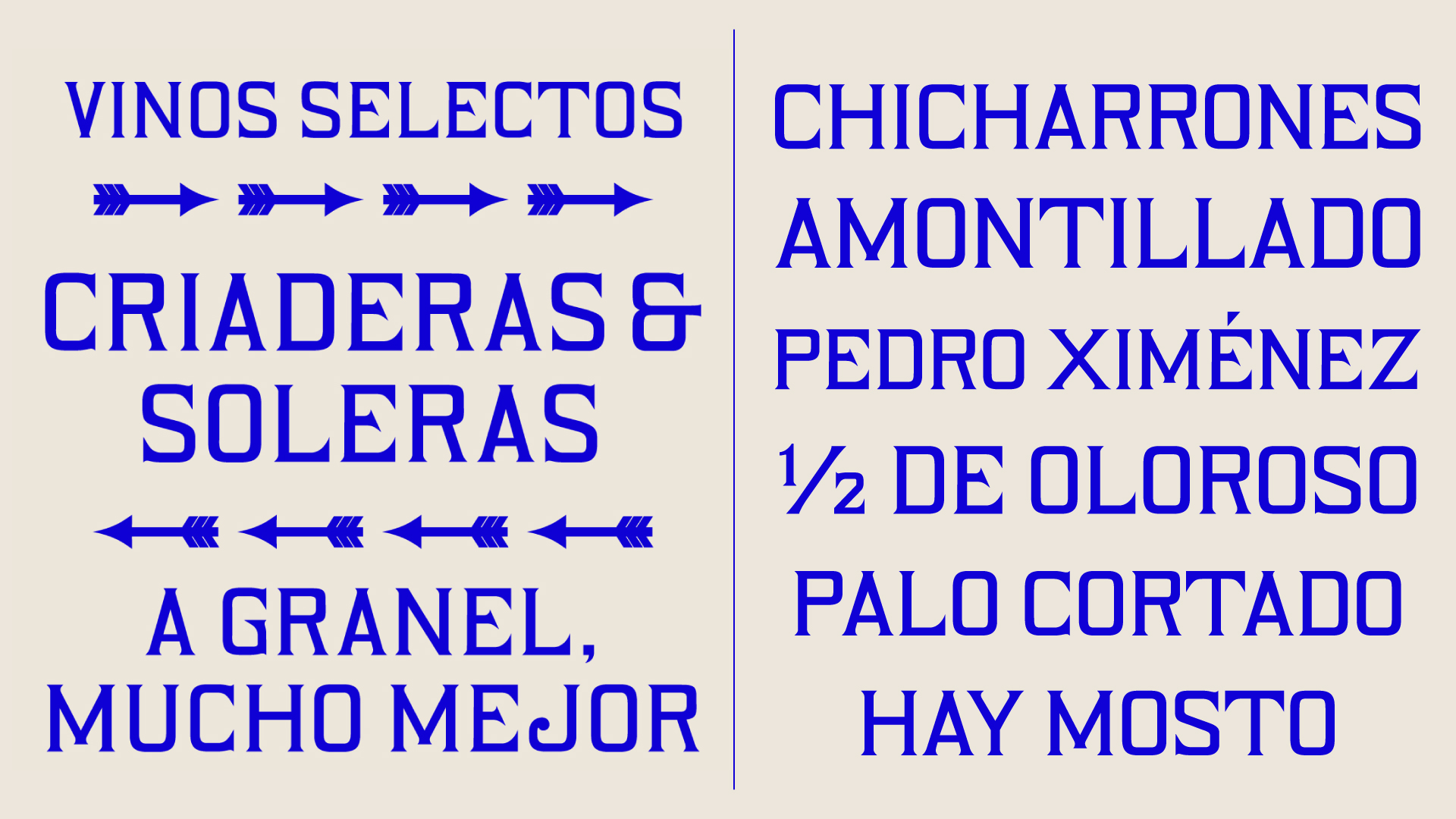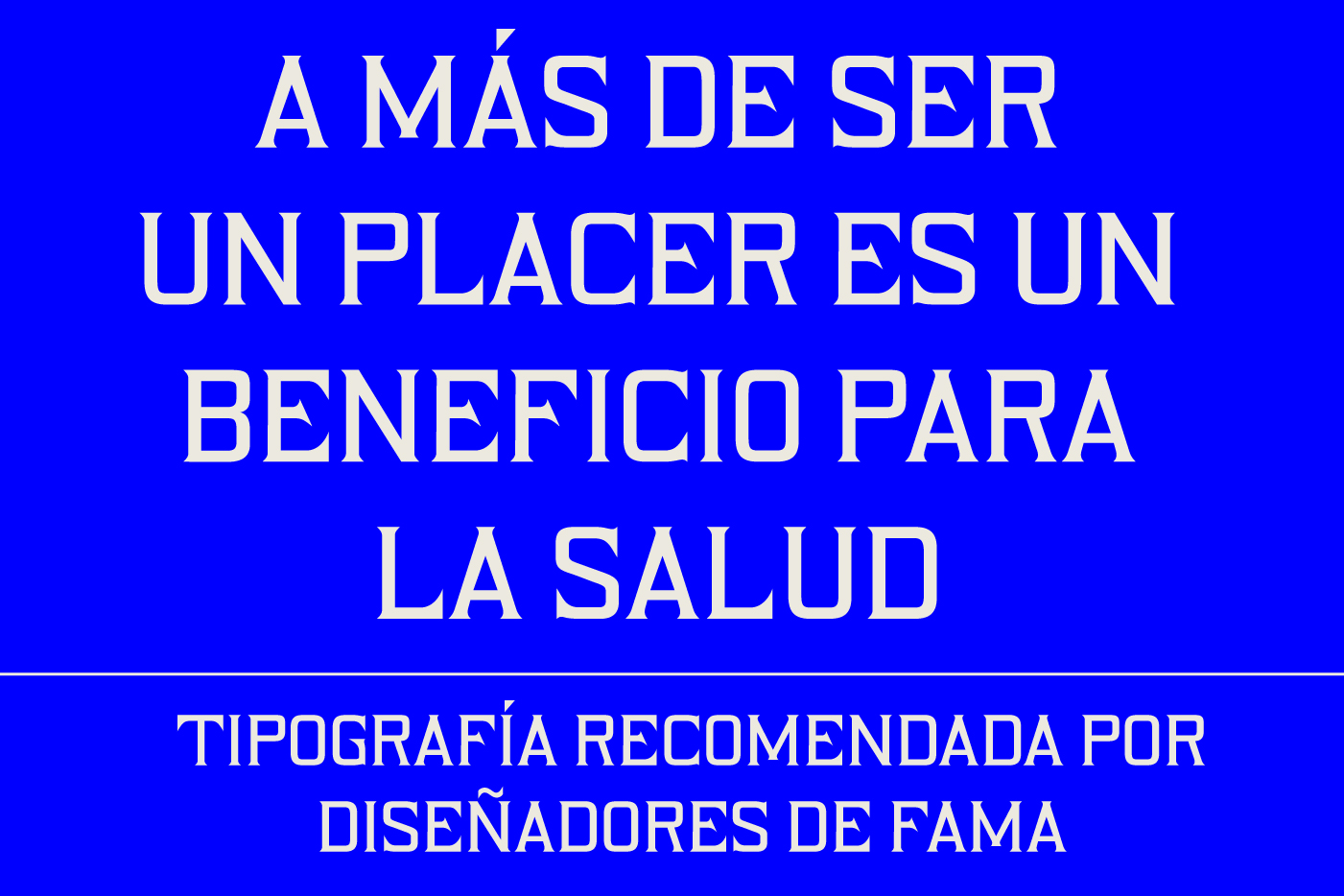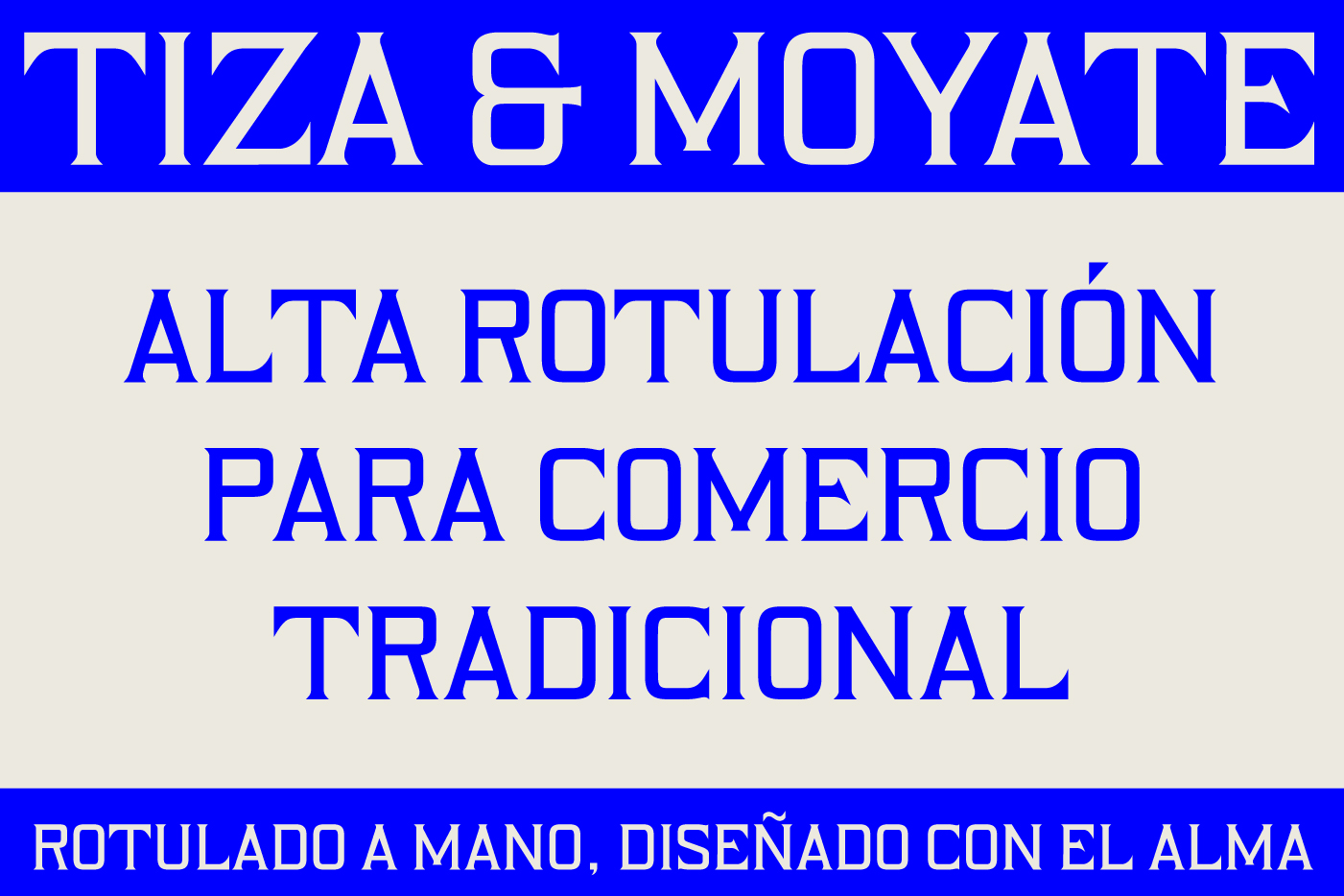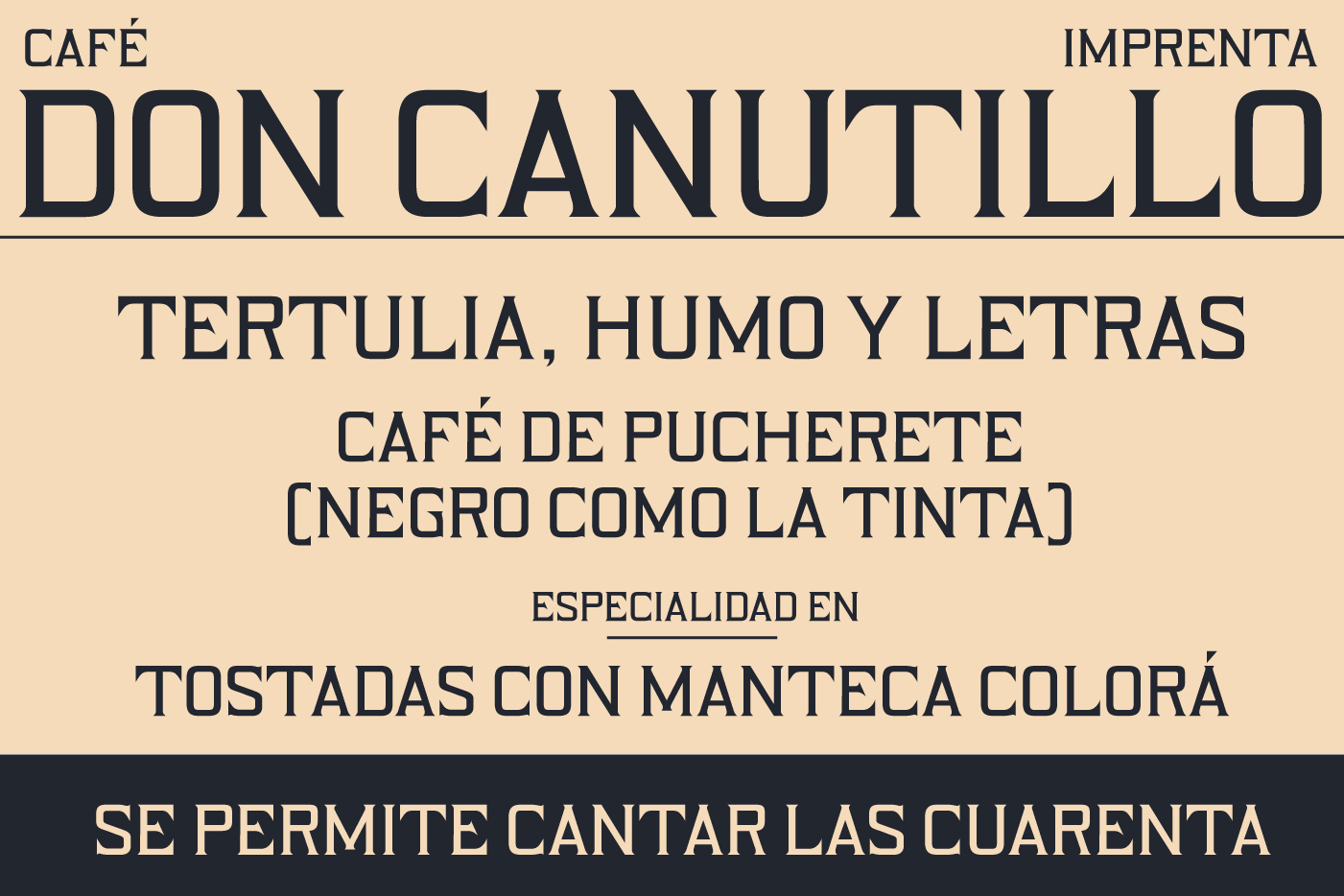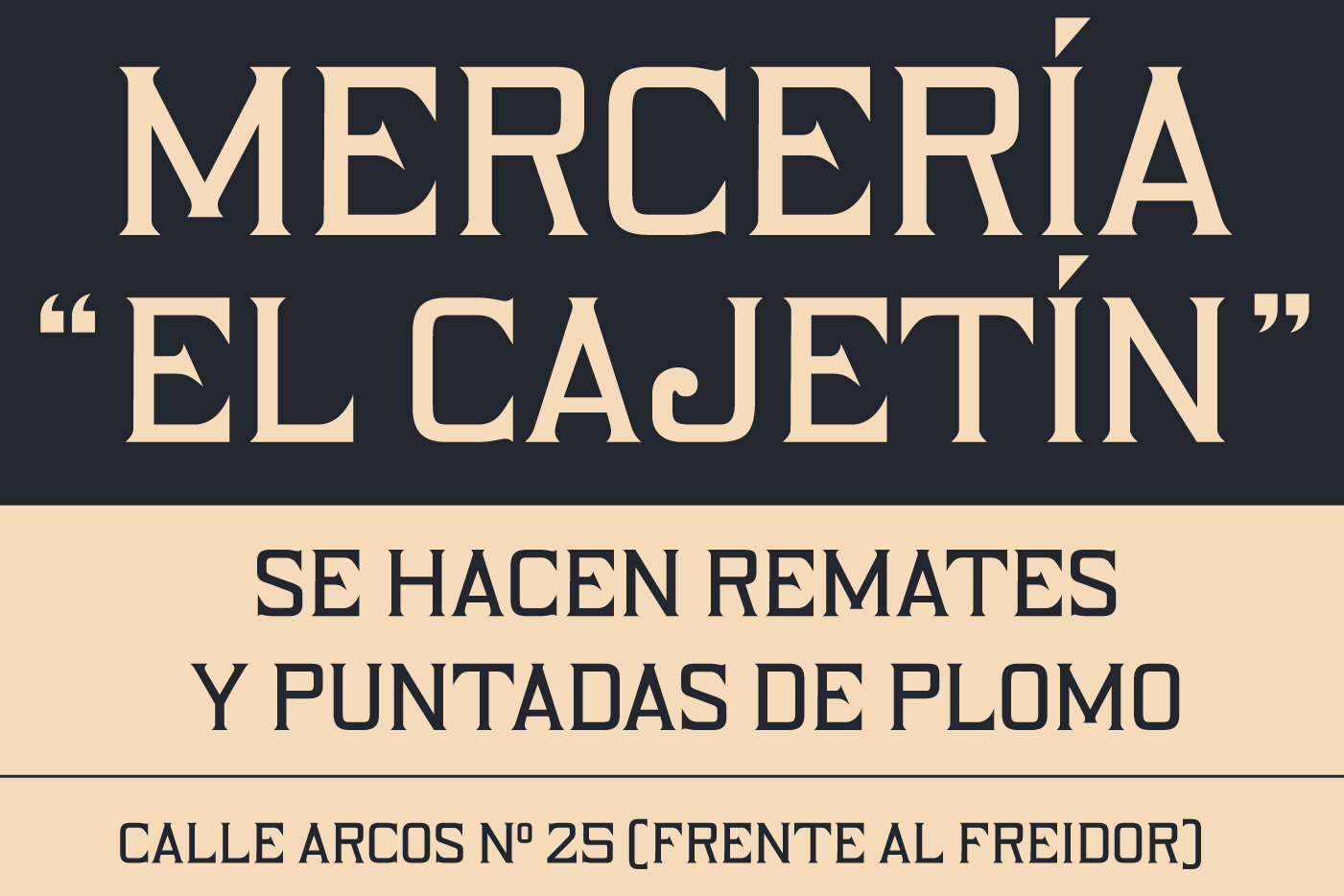
TABANQUERA
Rotulación tradicional
TABANQUERA
Rotulación tradicional
AQUÍ SE DESPACHA ROTULACIÓN DE NEGOCIOS CASTIZOS
Rotulación con denominación de origen
Tabanquera es la tipografía de nuestro catálogo que más habla sobre los antiguos negocios, despachos y tabancos tradicionales de Jerez. Una tipografía con serifas muy peculiares y con un estilo muy característico de la rotulación artesanal de la zona. Es una fuente que comunica honestidad, tradición y origen. Busca ser auténtica y directa.
Desde este Despacho de Tipos, no solo fundimos letras, sino que también queremos mantener ese estilo de rotulación característico de la zona. Sabemos que las fachadas hablan y generan identidad. Por eso, nos interesa trabajar y estudiar nuestra rotulación propia, esa que hacían los rotulistas a cambio de un vaso de vino, para seguir ofreciendo herramientas de gran valor tanto para los negocios tradicionales, como para los diseñadores modernos.
Se hacen rótulos por encargo
Para desarrollar Tabanquera, solamente nos hemos parado a observar. Cada día nos llegan cajas de fotografías al taller con rótulos antiguos y solemos ir ordenándolas conforme llegan. Al tiempo, nos percatamos que habían rótulos ubicados en calles paralelas que compartían elementos gráficos muy similares. ¿Será que lo habrá hecho el mismo rotulista? ¿Es moda o estilo? Fuese lo que fuese, lo que sabemos es que hubo un estilo normalizado y eso nos interesa. Estamos hablando de negocios como el mítico «Tabanco El Pasaje», «La Concepción, Viuda de Quevedo» o «Café Consistorio».
Del pincel al chibalete
Tabanquera es una es una tipografía que habla alto. Úsala usted en sus proyectos de diseño de etiquetas, para ponerla en el nuevo rótulo de su puesto de aceitunas o para los carteles de los recitales flamencos de la peña a la que perteneces.
Rotulación con denominación de origen
Tabanquera es la tipografía de nuestro catálogo que más habla sobre los antiguos negocios, despachos y tabancos tradicionales de Jerez. Una tipografía con serifas muy peculiares y con un estilo muy característico de la rotulación artesanal de la zona. Es una fuente que comunica honestidad, tradición y origen. Busca ser auténtica y directa.
Desde este Despacho de Tipos, no solo fundimos letras, sino que también queremos mantener ese estilo de rotulación característico de la zona. Sabemos que las fachadas hablan y generan identidad. Por eso, nos interesa trabajar y estudiar nuestra rotulación propia, esa que hacían los rotulistas a cambio de un vaso de vino, para seguir ofreciendo herramientas de gran valor tanto para los negocios tradicionales, como para los diseñadores modernos.
Se hacen rótulos por encargo
Para desarrollar Tabanquera, solamente nos hemos parado a observar. Cada día nos llegan cajas de fotografías al taller con rótulos antiguos y solemos ir ordenándolas conforme llegan. Al tiempo, nos percatamos que habían rótulos ubicados en calles paralelas que compartían elementos gráficos muy similares. ¿Será que lo habrá hecho el mismo rotulista? ¿Es moda o estilo? Fuese lo que fuese, lo que sabemos es que hubo un estilo normalizado y eso nos interesa. Estamos hablando de negocios como el mítico «Tabanco El Pasaje», «La Concepción, Viuda de Quevedo» o «Café Consistorio».
Del pincel al chibalete
Tabanquera es una es una tipografía que habla alto. Úsala usted en sus proyectos de diseño de etiquetas, para ponerla en el nuevo rótulo de su puesto de aceitunas o para los carteles de los recitales flamencos de la peña a la que perteneces.
| Origen: Rotulación negocios tradicionales de Jerez | Distribución: Despacho de Tipos |
Tabanquera
Tabanquera es nuestra tipografía con más ADN de los antiguos negocios y tabancos tradicionales de Jerez. 418 glifos en formatos .otf para versiones impresas y .woff para versiones digitales. Es una fuente que comunica honestidad, tradición y origen. ¡Utilice Tabanquera y dote a sus diseños de un carácter soberano!
Tabanquera
Tabanquera es nuestra tipografía con más ADN de los antiguos negocios y tabancos tradicionales de Jerez. 418 glifos en formatos .otf para versiones impresas y .woff para versiones digitales. Es una fuente que comunica honestidad, tradición y origen. ¡Utilice Tabanquera y dote a sus diseños de un carácter soberano!